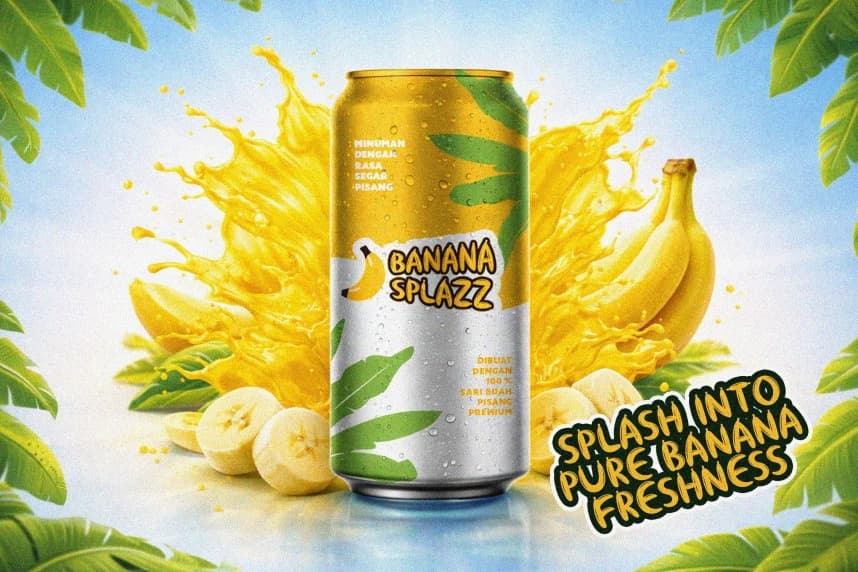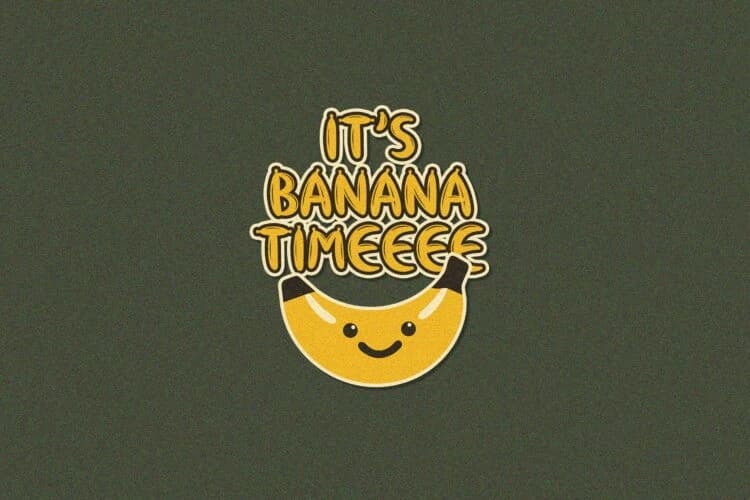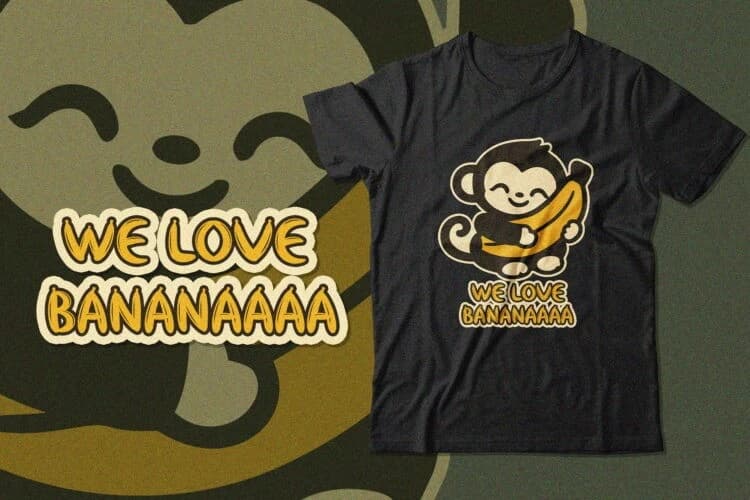
Banacake Playful Font
Banacake Playful Font, kalın ve yuvarlak hatlara sahip, eğlenceli ve ferah bir hava veren tropikal muz temalı bir fonttur. Muzların doğal eğrilerinden esinlenen bu yazı tipi, tasarımlarınıza neşeli ve dikkat çekici bir kişilik kazandırır.
Banacake Playful Font, kalın ve yuvarlak hatlara sahip, eğlenceli ve taze bir hava veren tropik muz temalı bir fonttur. Muzların doğal eğrilerinden ilham alan bu yazı tipi, tasarımlarınıza neşeli ve dikkat çekici bir kişilik kazandırır.